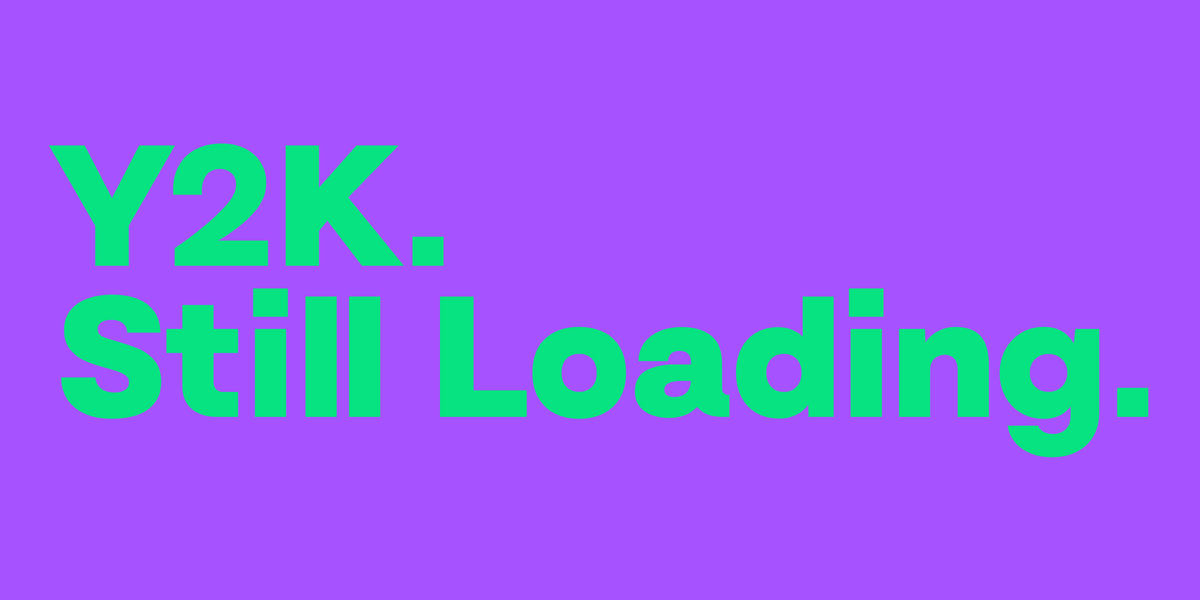
5 fuentes Y2K que recuerdan la estética de principios de los 2000
Y2K. Still Loading. Set in Bitec by Mojomox
Las fuentes Y2K son un elemento de diseño clave de la estética Y2K, que surgió a fines de la década de 1990 y principios de la década de 2000. Estas fuentes se caracterizan por sus diseños audaces y cuadrados con ángulos pronunciados y formas geométricas, lo que les da una sensación futurista.
La estética Y2K ha experimentado un aumento de popularidad en los últimos años y muchos diseñadores gráficos han incorporado elementos Y2K en su trabajo.
1. Fuente Lace en grosor de fuente negro, letras minúsculas
Fuente de encaje en minúsculas y peso de fuente negro
La tipografía manuscrita siempre ha estado de moda. Para añadir un toque Y2K a cualquier diseño, simplemente elija el grosor de fuente más grueso y considere cambiar el título a letras mayúsculas o minúsculas para reflejar la "ortografía de Internet" de los años 2000. Obtenga Lace Black aquí .
Cualquier color rosa intenso o magenta es perfecto, especialmente si se combina con verdes neón o brillantes. Espolvorea algunos corazones o estrellas: los diseños planos y en 3D combinan a la perfección.
2. Fuente Sway en grosores de fuente más negrita y letras mayúsculas
Fuente Sway en grosores de fuente más negrita y letras mayúsculas
Mantengámonos en la paleta de colores verde brillante y conservemos un poco de rosa, pero agreguemos un azul medio para este próximo diseño Y2K. La tipografía Sway es súper futurista tanto en mayúsculas como en minúsculas. Estos titulares ondulados pueden ser difíciles de leer, pero eso es parte de la estética millennial. Las diagonales de los tallos de las letras están en el mismo ángulo para que las palabras y los logotipos se vean geométricos y simplemente geniales al estilo Y2K. Si lo desea, enmarque su diseño con un borde grueso con esquinas redondeadas y agregue íconos de Internet de etapa temprana utilizando caras sonrientes, globos terráqueos y flechas.
3. Skay Black en letras mayúsculas con contornos
Skay Black en letras mayúsculas con contornos
¿Hay alguna ocasión en la que una fuente de burbujas no sea la tipografía adecuada? ¡Sí, la hay! Pero no cuando se trata de finales de los 90. Haz que la tipografía sea llamativa (como Skay Black ), añade uno o dos bordes y utiliza paletas de colores de alto contraste, como negros y rosas. Patrones de semitonos o grafitis: el estilo grunge es la mejor opción para crear diseños Y2K.
4. Loco, fuente burbuja en letras mayúsculas
Loco, fuente burbuja en letras mayúsculas
Otra fuente de burbujas que funciona bien para los gráficos de la generación del milenio es la tipografía Loco . Viene con detalles para dar un efecto 3D aún más fuerte. Loco nos recuerda los tiempos divertidos con globos retorcidos, especialmente cuando agregas un borde más grueso a tu título. Esta paleta de colores que usa amarillo, rosa y negro es brillante y retro al mismo tiempo.
5. Fuente Goji en minúsculas y grosor de fuente negro
Goji, fuente redondeada en mayúsculas y contorno
Otra tipografía redondeada es Goji , una versión más relajada que la tipografía Loco. Goji luce muy bien en un estilo de contorno, escrito en mayúsculas.
La necesidad de velocidad y digitalización
Las fuentes Y2K son una combinación única de estilos retro y futurista. Las mayúsculas y las esquinas redondeadas, las letras con forma de cuenco desplazadas y las líneas onduladas en todas las letras mayúsculas y minúsculas son características comunes de las fuentes.
Estilos de tinta, píxeles y grafitis, contornos de fuentes y tipos inclinados: todo quedó decorado con estrellas, destellos y swooshes, elementos de diseño populares durante el cambio de milenio.
Si eso es suficiente, piense en una estética cibernética techno incrustada en un marco atrevido y salpicada de corazones.
Paletas de colores que resaltan más que los fuegos artificiales
¡Las paletas de colores del año 2000 eran audaces! Neón, negro, rosa, metales... Piensa en cualquier color que salga de una lata de aerosol para grafitis y estarás listo. Un estilo de color brillante y resplandeciente al estilo de una muñeca Barbie también funciona bien con las paletas del año 2000.